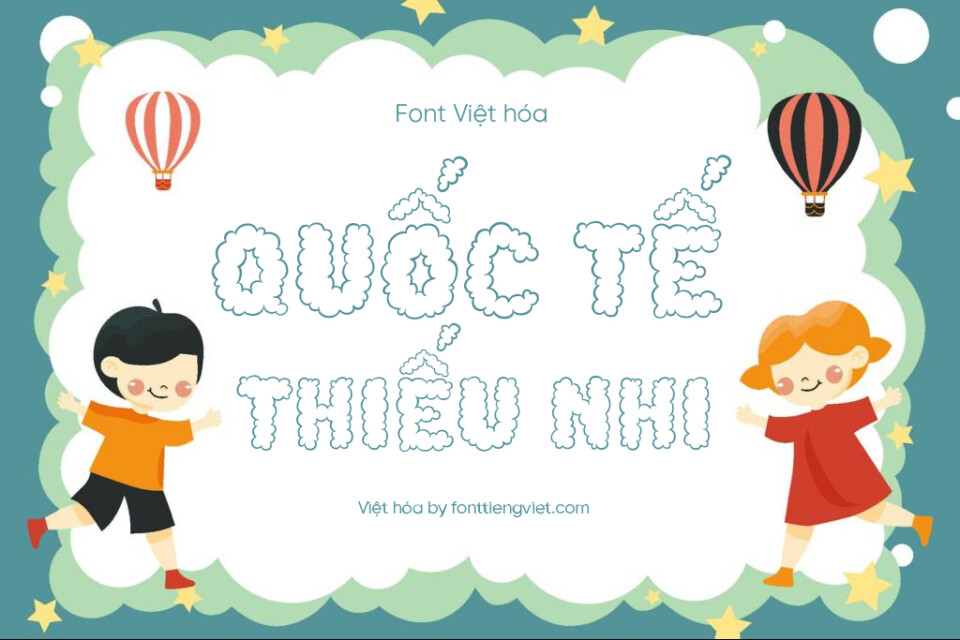
Font Việt hóa 1FTV Cotton Cloud
Giới thiệu về Font Việt hóa 1FTV Cotton Cloud
Trong thế giới thiết kế đồ họa dành cho lứa tuổi học đường, việc lựa chọn một Font Miễn Phí phù hợp là yếu tố then chốt để tạo nên sự thu hút. Font Việt hóa 1FTV Cotton Cloud nổi lên như một lựa chọn hoàn hảo với phong cách nhẹ nhàng, mềm mại như những đám mây bông. Đây là bộ phông chữ được tinh chỉnh kỹ lưỡng về dấu tiếng Việt, giúp các bạn học sinh và thầy cô dễ dàng ứng dụng vào các bài thuyết trình, thiệp chúc mừng hay báo tường mà không lo lỗi hiển thị.
Đặc điểm nổi bật của bộ font chữ này
Điểm ấn tượng nhất của Font Việt hóa 1FTV Cotton Cloud chính là những đường nét bo tròn và cấu trúc chữ viết tay tự nhiên. Kiểu dáng này mang lại cảm giác thân thiện, gần gũi, giúp nội dung truyền tải trở nên sinh động hơn. Ngoài ra, bộ font còn hỗ trợ đầy đủ các ký tự đặc biệt, giúp tối ưu hóa quá trình soạn thảo văn bản tiếng Việt một cách trơn tru nhất.
Ứng dụng Font Việt hóa 1FTV Cotton Cloud trong học tập
Các bạn học sinh có thể sử dụng Font Việt hóa 1FTV Cotton Cloud để trang trí tiêu đề bài học hoặc làm nổi bật các ý chính trong sơ đồ tư duy. Đối với giáo viên, đây là công cụ đắc lực để thiết kế các phiếu bài tập sáng tạo hoặc slide bài giảng điện tử, giúp các em nhỏ hứng thú hơn với việc học tập mỗi ngày.
Kết luận về bộ font chữ độc đáo